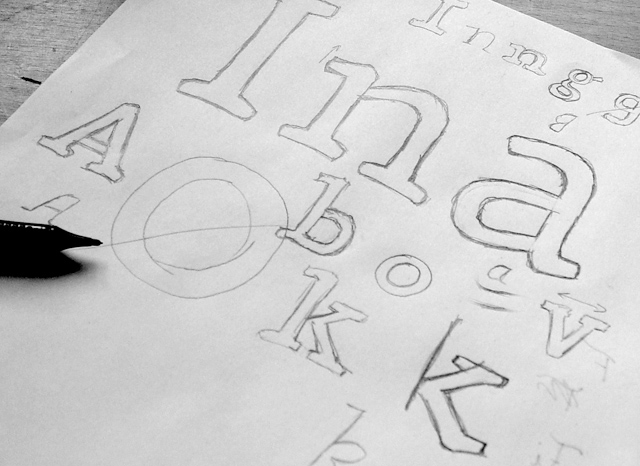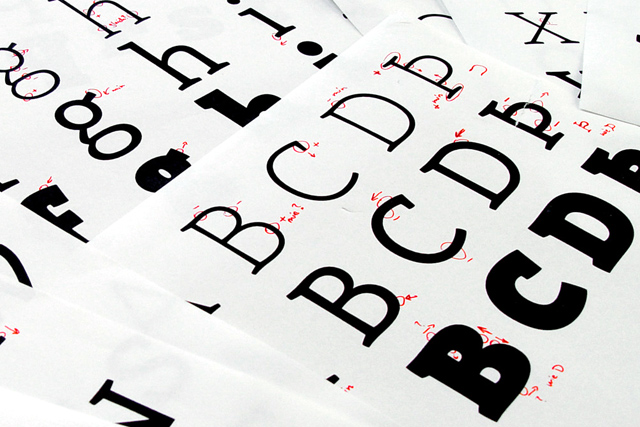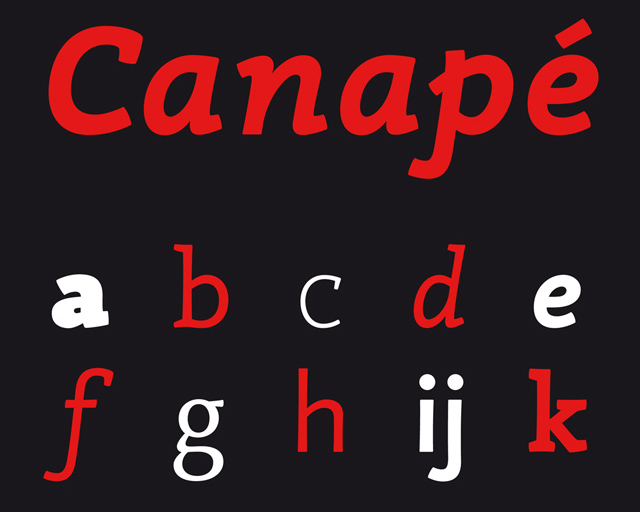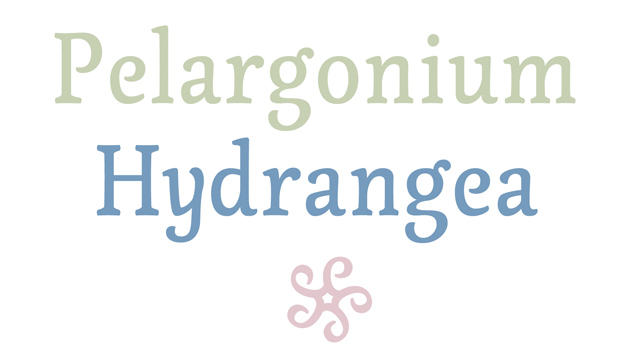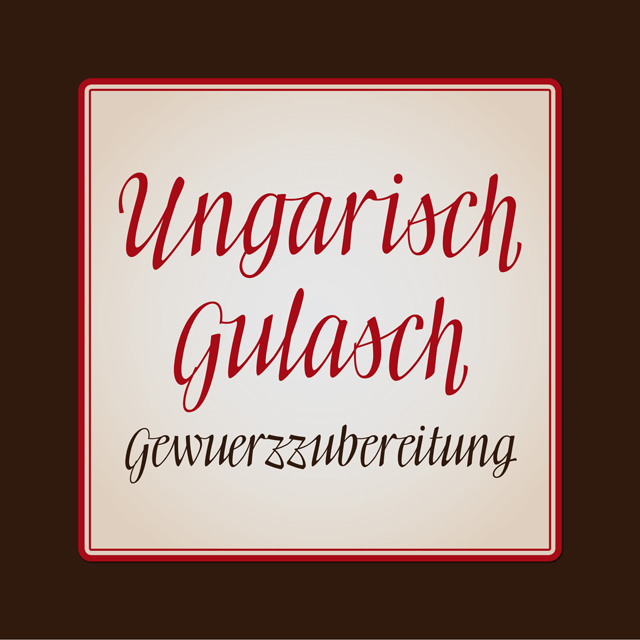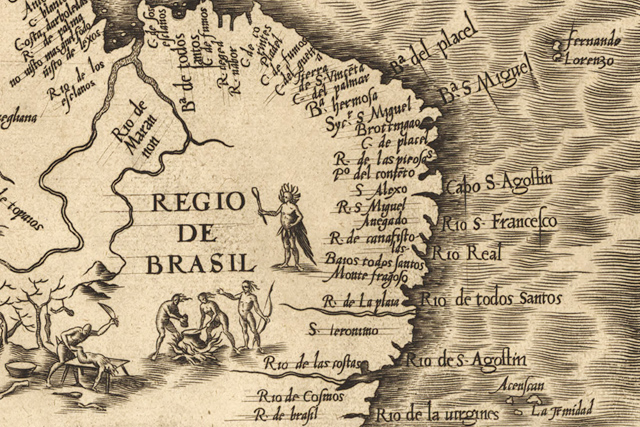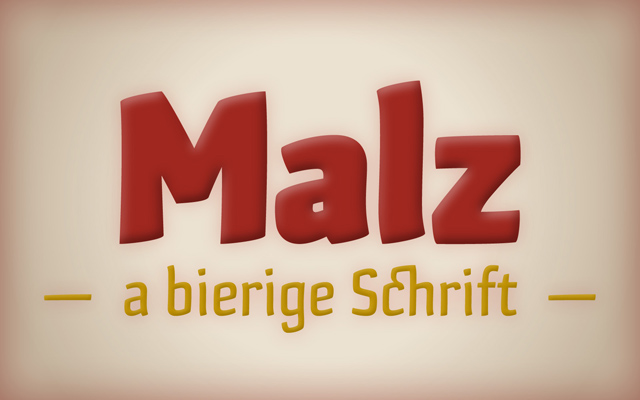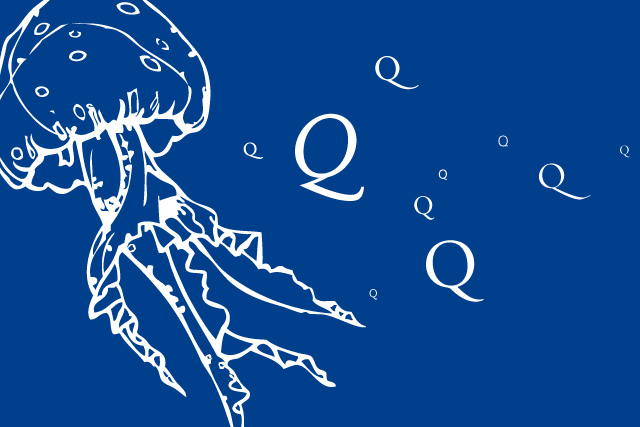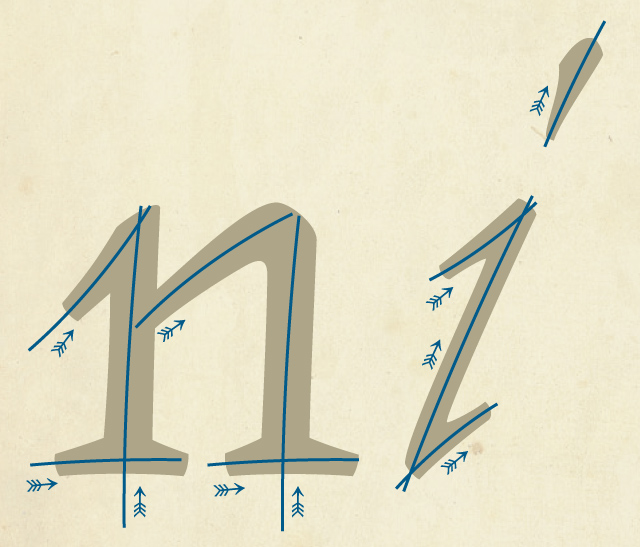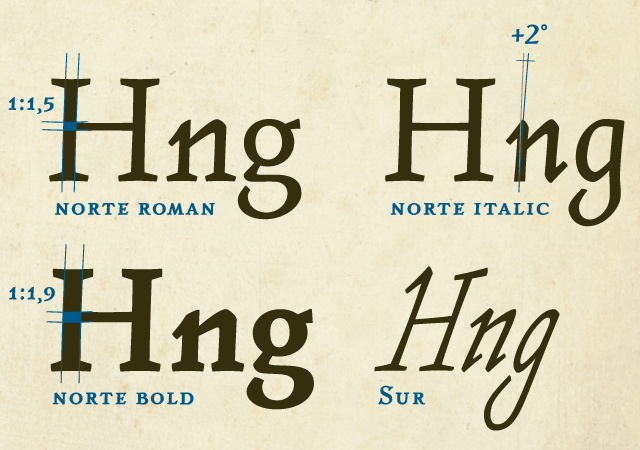
Interview mit Sebastian Nagel
Sebastian Nagel (*1981) studierte intermediale Kommunikationsgestaltung (»Intermedia«) an der Fachhochschule Vorarlberg, und arbeitet heute als angestellter Grafiker sowie freischaffender Grafiker und Schriftgestalter in Lustenau und Dornbirn, Österreich. In diesem Interview befragten wir ihn zu Techniken und Ansichten bezüglich des Schriftdesigns im 21. Jahrhundert.
Wie bist Du zur Typografie und zur Schriftgestaltung gekommen?
Ganz ursprünglich mit meinem ersten Kontakt zu einem Computer, und über eine fabelhafte Shareware-CD-ROM »10.000 Schriften für zehn Mark« aus dem lokalen Supermarkt – natürlich völliger Schrott, die Vielfalt und die Einsatzmöglichkeiten haben mich aber doch fasziniert.
In meinem Studium für Mediengestaltung habe ich mich dann im Grundstudium recht schnell für Typografie und Schrift interessiert. Typografie bot mir als junger Einsteiger ein ausgewogenes Verhältnis zwischen Freiheit und Konvention, Gestaltungsfreiheit bei doch klar definierten Kriterien. Als Anfänger hatte ich dadurch ein paar Orientierungspunkte und verlief mich nicht im weiten Feld des spontanen, emotionalen oder freigeistigen grafischen Experiments. Dem einen oder anderen Dozenten war ich damit bestimmt zu wenig »wild«, zum Glück gab es aber auch jene, die mich in meiner eher analytischen und systematischen Richtung bestärkt und mein Interesse richtig geweckt haben. Nach acht Semestern habe ich dann als Diplomarbeit »langatmige und öde Schriftanalysen« (Zitat eines Prüfers) abgeliefert, und mich eigentlich erst danach an Schriftgestaltung selbst gewagt.
Experimentelle Studentenarbeiten (freie Arbeiten zum Buchstaben »Q«)
Welche Rolle spielen analoge und digitale Werkzeuge in Deiner Arbeit als Schriftgestalter – wie entwickelst und prüfst du deine Fonts?
So gerne ich antworten würde, dass ich erst kalligrafische Experimentreihen starte, eine Hand-Stift-Papier-Urform ermittle und erst am Ende eines langen Prozesses das Ganze dann noch in eine digitale Form übertrage … die Realität sieht eher so aus, dass ich nach einer Initial-Idee vier bis fünf Buchstaben in einem Notizbuch skizziere, mich etwas über mein handwerkliches Unvermögen ärgere und dann das Vorhaben recht schnell auf den Computer übertrage, wo ich an den Details herumtüfteln kann, bis sie genau meinen Vorstellungen entsprechen. Die analoge Skizze ist dabei »nur« eine wichtige Gedankenstütze, um meine erste Vorstellung in Erinnerung zu halten.
Nach dem Entwurf eines Basis-Alphabets im Fonteditor ist – parallel zum weiteren Ausbau – die erste Testumgebung ein typografisches Anwendungsprogramm, wo ich ein erstes Schriftmusterbuch mit Testtexten und Zeichensammlungen erstelle, um die Schrift im Einsatz zu erproben. Selbst wenn eine Schrift am Ende gedruckt auf Papier erscheint, beschäftigt sich ein Setzer zuvor schon lange und intensiv mit ihr in seiner Setzerei (die heute eben digital ist). Als Typograf weiß ich aus meinem täglichen Umgang mit anderen Schriften, wie sich diese in der Anwendung »anfühlen« – sowohl optisch als auch programmiertechnisch (Opentype betreffend). Grobe Ungereimtheiten fallen in dieser Umgebung meist schon deutlich auf und können in der nächsten Version des Fonts korrigiert und gleich wieder getestet werden.
Nach größeren Korrekturgängen mache ich auch immer wieder Testdrucke, teilweise in Lesetextgröße, oft aber auch deutlich größer. Die eigentliche Begutachtung und jeder Detail-Korrekturvermerk erfolgt dann analog auf Papier. Auf diese Weise finde ich deutlich mehr Detailfehler und kann Proportionen, Strichstärkenunterschiede, Winkel, etc. deutlich besser einschätzen als am Bildschirm selbst.
Wird eine Schrift langsam praxistauglich, versuche ich, sie in einem realen Projekt einzusetzen und möglichst auch hochwertig zu drucken. Das gibt mir die Möglichkeit, die Schrift auch auf richtigen Druckmaschinen und entsprechendem Papier testen zu können.
Vor der eigentlichen Veröffentlichung gestalte ich dann das im Prozess angelegte Schriftmusterbuch noch einmal von Grund auf neu. Dabei versuche ich, die Schrift konsequent genau so zu verwenden, wie sie im Font abgelegt ist – also ohne durch Setzer-Korrekturen nachträglich zu »optimieren«. Was im Schriftmuster zur Schrift zu sehen ist, ist bis auf ganz wenige notwendige Details genau das, was auch im Font enthalten ist.
Die Iwan Reschniev entstand direkt aus Diskussionen aus der Typografie.info-Community und Du hast Deine Schriften meist auch schon in Entwurfsstadium auf Seiten wie Typophile.com oder Typografie.info präsentiert. Welche Rolle spielt dieses Feedback für Dich? Kann das Internet heute den persönlichen Lehrmeister ersetzen?
Als Einsteiger, der sich in diesem Bereich einfach aus Interesse einarbeiten wollte, war das Internet eine großartige Möglichkeit, ohne demotivierend großen Aufwand Rückmeldungen zu Entwürfen zu erhalten, Detailfragen beantwortet zu bekommen und sich vor allem auch Projekte anderer Gestalter in allen Entwicklungsstadien und Qualitätsstufen anzusehen.
Eine besonders effiziente Lernmethode und -hilfe ist das Internet aber nicht – die Rückmeldungen sind naturgemäß alle auf freiwilliger Basis, haben unterschiedliche Qualitäten und Motivationen, und es sprechen sehr viele Stimmen mit unterschiedlichen Meinungen zu einem.
Was mir allerdings weiterhin sehr viel nützt ist, in den Experten-Foren auftauchende Detail-Fragestellungen aktiv mitzudiskutieren (zum Beispiel die vor kurzem entstandene Diskussion auf Typografie.info über die »richtige« Ausrichtung des @ zur Grundlinie). Die Beschäftigung mit solchen Details schärft laufend mein Bewusstsein – und beim nächsten @-Zeichen das ich gestalte, habe ich wieder in Erinnerung, was Anwendern in der Praxis wichtig ist, was Konsens findet, was abgelehnt wird …
In Skizzenform liegen im Projekt-Ordner noch »Gulasch« – eine altmodische, feine Script, die vermutlich noch viel Arbeit erfordert – und »Flora« – eine blumige Antiqua, die bisher noch nicht so recht weiß, ob sie Display- oder Leseschrift sein soll) … Wann und wie ich diese weiterentwickeln werde, steht noch in den Sternen.